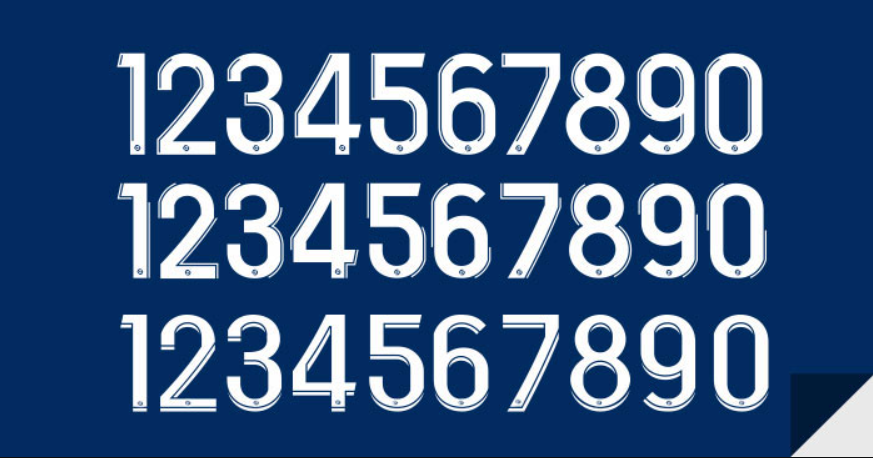
O Campeonato Francês (conhecido como Ligue 1 Uber Eats nesta temporada) adota um padrão visual unificado. Isso significa que, independentemente da marca do uniforme — seja a Nike do PSG, a Puma do Olympique de Marseille ou a Adidas do Lyon — a tipografia utilizada nas costas das camisas para nomes e números é exatamente a mesma.
Estilo Visual e Design
A tipografia da Ligue 1 2023-24 segue uma estética moderna, sólida e geométrica. Diferente de temporadas anteriores que apostavam em curvas mais complexas, a versão atual foca na legibilidade e impacto visual.
- Traços: Linhas retas e cortes diagonais sutis que trazem dinamismo.
- Identidade: Os números geralmente carregam o logotipo da liga (o hexágono estilizado) na base, um detalhe que incluímos na versão vetorizada deste pacote.
- Aplicação: Embora a fonte seja única, cada clube personaliza a aplicação com cores internas, bordas (strokes) ou texturas específicas dentro dos números para combinar com o kit (Home, Away ou Third).